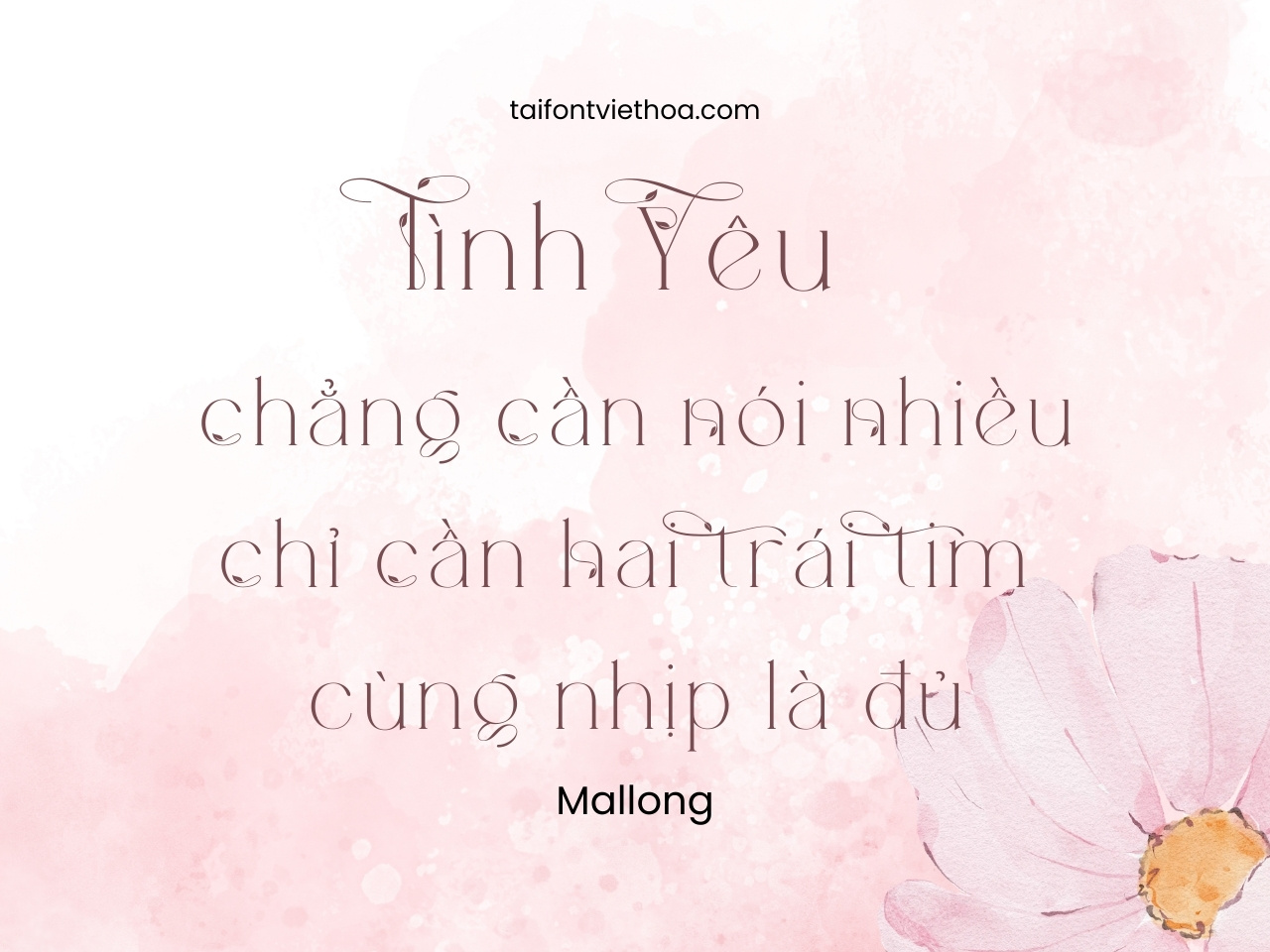
Font việt hóa Mallong Regular
Giới thiệu font Mallong Regular – Kiểu serif hiện đại của Kana Widana
Mallong Regular là một kiểu font serif hiện đại mang âm hưởng hoài cổ, được thiết kế bởi Kana Widana. Font kết hợp giữa tính lịch thiệp của serif cổ điển và đường nét thanh thoát của thiết kế đương đại, giúp nó trở thành lựa chọn lý tưởng cho các dự án cần sự sang trọng và chuyên nghiệp. Phiên bản Việt hóa đã được thực hiện đầy đủ, hỗ trợ tiếng Việt và hơn 80 ngôn ngữ khác. Font này đã được taifontviethoa.com sưu tầm và chọn lọc để phục vụ cộng đồng thiết kế yêu thích các kiểu chữ có chiều sâu, mang tính ứng dụng cao trong branding, trình bày và thiết kế sáng tạo đa lĩnh vực.
Đường nét thanh lịch và ứng dụng của Mallong Regular
Mallong Regular sở hữu phần chân chữ chắc chắn, thân chữ cao, các nét thanh đậm xen kẽ hài hòa, tạo nên sự ổn định trong trình bày mà không đánh mất tính thẩm mỹ. Font phù hợp để sử dụng trong thiết kế logo thương hiệu cao cấp, tiêu đề sách, giao diện web, tài liệu marketing, bao bì sản phẩm thủ công hoặc mỹ phẩm. Các ngành nghề phù hợp bao gồm giáo dục, bất động sản, quảng cáo, truyền thông và thời trang. Mallong Regular cũng là lựa chọn lý tưởng cho các sự kiện như sinh nhật thương hiệu, chiến dịch Valentine, lễ hội mùa xuân hoặc các hoạt động truyền thông thương hiệu mang tính thanh lịch và hiện đại.